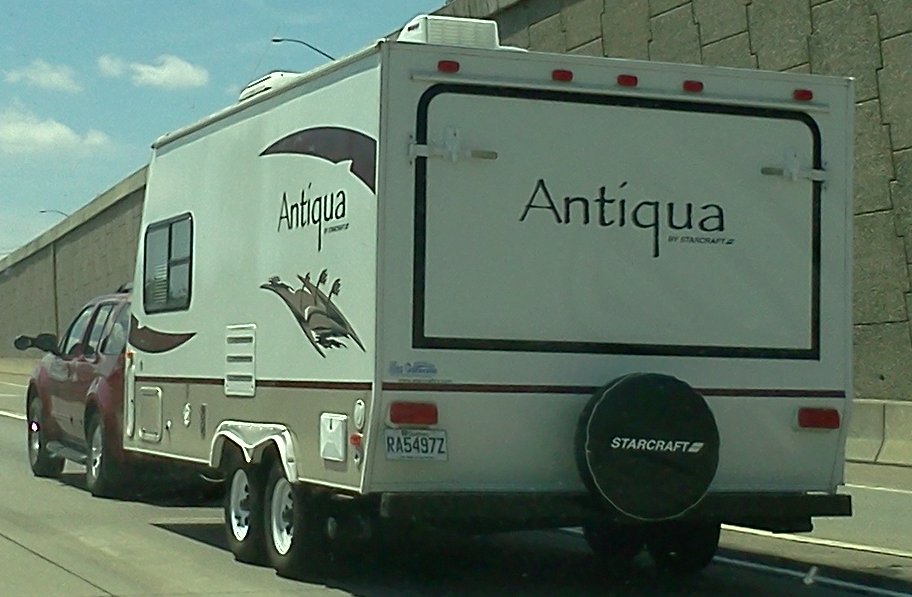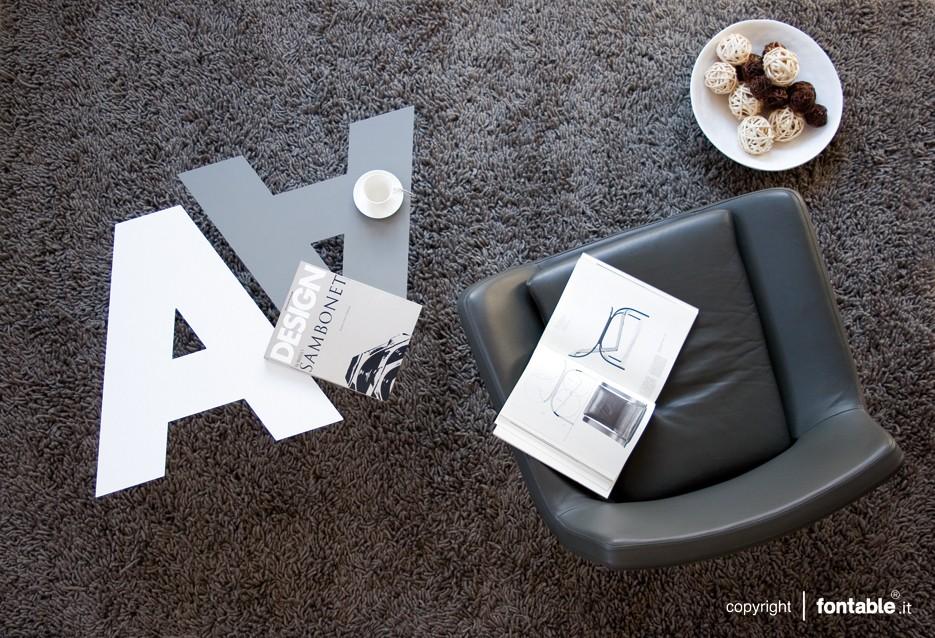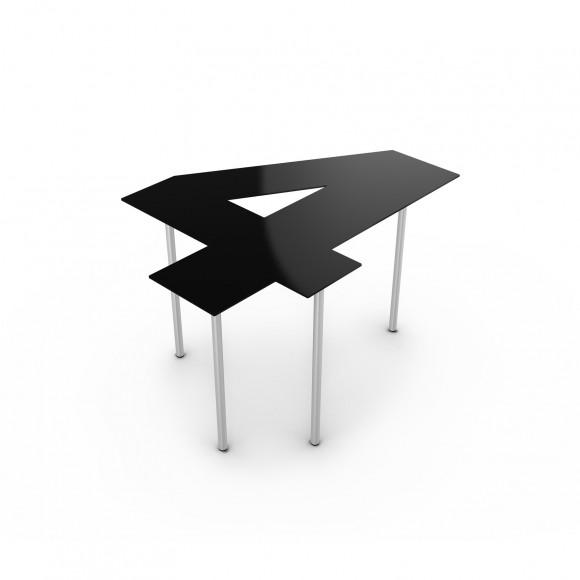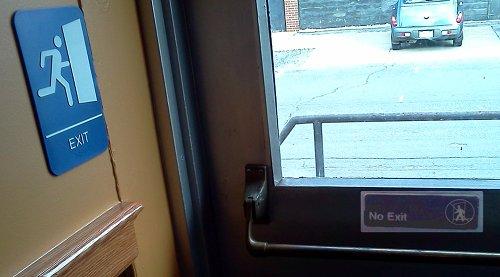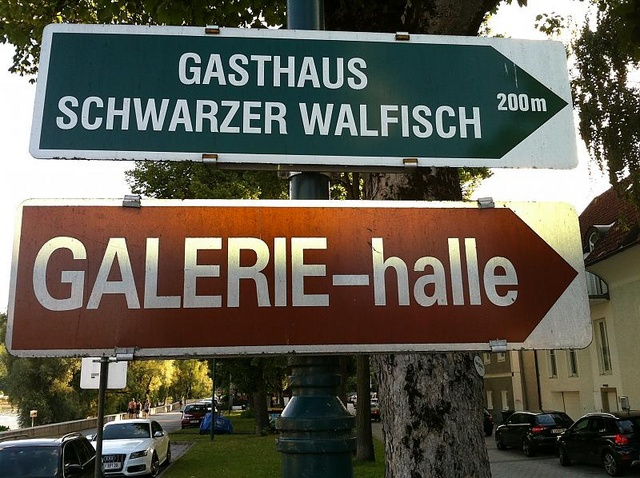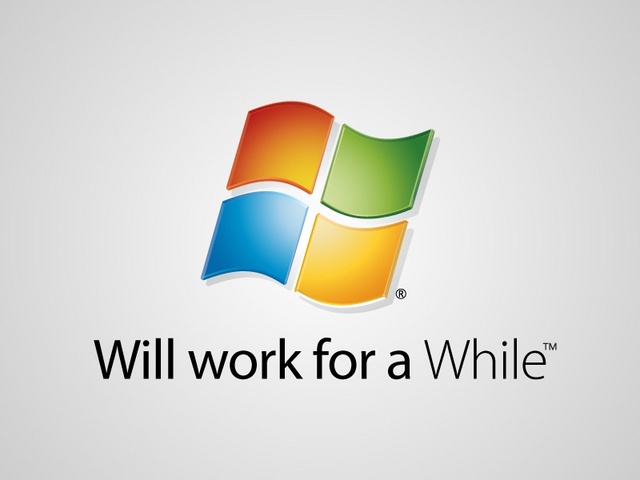
Wenn man den Rest der Lokalität in diese Überlegungen mit einbezieht, kommen einem Sachen wie »genialer Schachzug« nicht in den Sinn.
Uns nicht. Dem Ersteller vielleicht schon :-)
Beim Spazieren in Linz gefunden ...
Ich habe allerdings noch nicht recherchiert, ob das ein Eigenname ist :-?
Gestern auf der Interstate in Pennsylvania:
Klick aufs Bild zeigt den Wohnwagen, auf dem dieser Schriftzug steht
Vorhin beim Vietnamesen: :-?
Falls es aus dem Bild nicht klar hervorgehen sollte: es gibt nur eine Tür.
Logos bekannter Marken wollen viel ausdrücken, doch sie sagen meistens aber nur die halbe Wahrheit. Der schwedische Künstler Viktor Hertz verfremdet in seiner grafischen Serie "Honest Logos" weltweit bekannte Schriftzüge. Dafür spielt er ironisch mit den Erwartungen und Illusionen, die Marken transportieren. Herausgekommen sind Vorschläge, wie die großen Konzerne eigentlich heißen sollten.
Da bin ich auch erst neulich dran vorbeigehüpft, Martin,
die Augen im Wellenanschlag auf diese Fassade geheftet.
Ich frage mich ja schon seit Jahrzehnten, was es mit dem Geschrei um das Italian Design auf sich haben mag. Tatsächlich sind diese Tische ja noch unpraktischer als ein Ferrari. Da landet doch jede zweite Caffè-Tasse im A-Loch (und so weiter …).
Es gibt halt "Wohnungen", die rein zu Schauzwecken unterhalten werden. Genauso wie Küchen mit einer sechsstelligen Auftragssumme höchst selten zum Kochen verwendet werden, und wenn, dann wird ein Profikoch irgendeinen Hokuspokus zelebrieren, den er aber in der Arbeitsküche im Nebenraum vorbereitet hat. Zum Anschauen sind die Möbel also ganz nett … und nach einem halben Jahr wird aus Langeweile wieder umdekoriert, dann ist plötzlich wieder Biedermeier angesagt.
Mir gefallen die »A«-Tische eigentlich ziemlich gut – mit einer Glasplatte drauf wäre auch das Kaffeetassenbermudadreiecke gebannt. Aber bei der 4 bin ich skeptisch: Der Tisch sieht mir ausgesprochen kippelig aus. Ich hätte die Beine anders verteilt. Außerdem stößt man sich bestimmt dauernd an so einer hakeligen 4. ;-)
Nachtrag: Außerdem sind mir die Beinchen zu kümmerlich …
Da landet doch jede zweite Caffè-Tasse im A-Loch (und so weiter …).
Dafür ist ja dann die Design-Buch-Deko da, mit der man das „Loch“ dann verschließen kann. :lol:
Es geht auch weniger „hakelig“ – aber dann umso „löchriger“. ;-)
Einer unserer Chefs würde sagen: „Designsch…“
Ich glaube, ich fände es cooler, wenn sich die Buchstabenform aus dem gleichen Material wie die Beine auf dem Boden noch mal wiederholt und wenn deutlich mehr Beine (gerne auch im Zickzack) die Platte und den Bodenbuchstaben verbinden – mehr wie eine Skulptur (unter solche ienen Tisch muss je eh keiner seine Füße drunterstellen). Die hier gezeigten Beine verströmen so ein bisschen Campingtisch- oder Schnellimbissatmosphäre. ;-)
Schnellimbissatmosphäre. ;-)
Gute Idee! So möbliert gründen wir doch unverzüglich die Alphabetaburger-Kette. (Klar gibt's dann dort auch Buchstabensuppe im Pappbecher.) Und vielleicht leiht uns Ralf die Rechte am irgendwie passenden Logo?
Und wenn wirs geschickt anstellen, dann bekommen wir das als Alphabetisierungsprojekt auch noch von der EU gefördert :nicken: